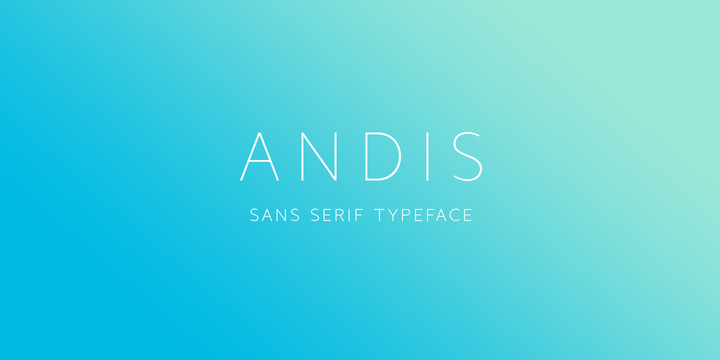
Andis Font Family – Download Grátis
Introduzimos a nova família de tipos de letras. Andis Font Family foi criada e compartilhada pela JAM Type Design. O grosso dos traços do Andis torna-o um tipo interessante para destaque, mas graças à sua altura x generosa e serifas firmes, o Andis funciona igualmente bem em tamanhos de texto. A itálica idiosincrática deste tipo constrói uma forte contraste com o romano. O Andis é tanto funcional quanto expressivo; seu uso dá um toque humanista à propaganda ou publicidade. A família de fontes é aperfeiçoada para textos em tamanhos variados, enquanto ainda mantém a sua aparição robusta e elegante no estilo sans-serif. A escolha da Andis traz uma camada mais profunda ao seu design editorial ou publicitário, adaptando-se com facilidade às necessidades de seus ambientes de uso.